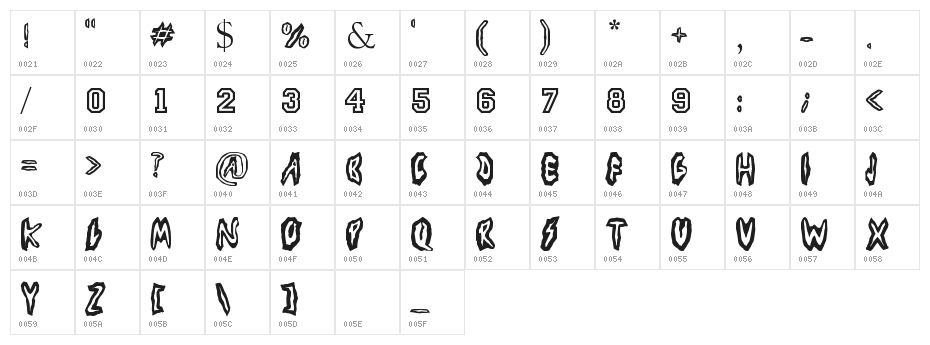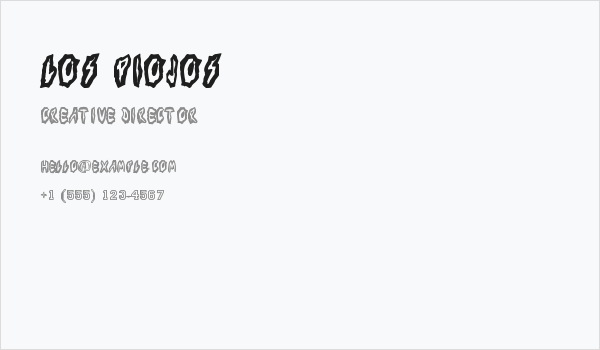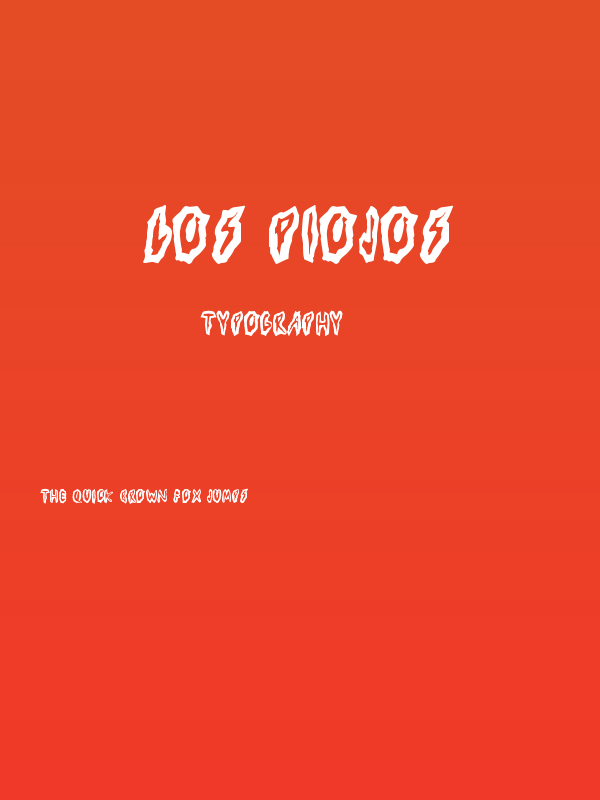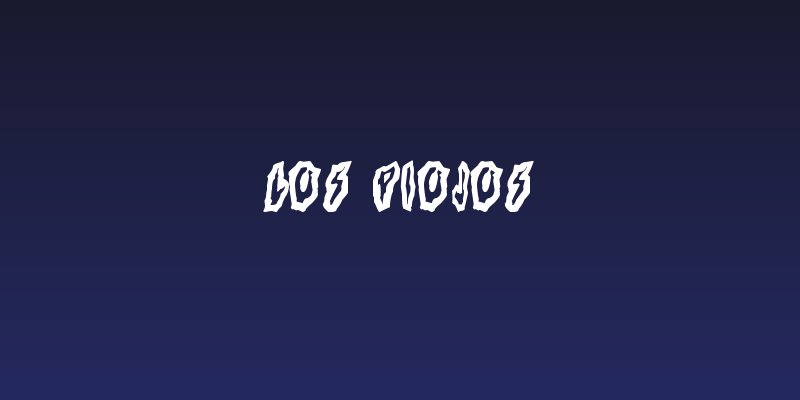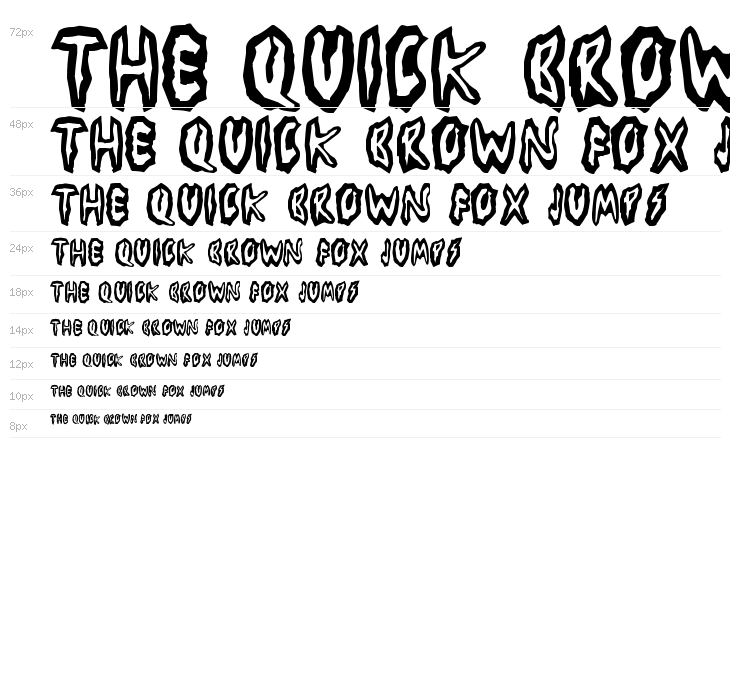
Los Piojos Font
✎ Distorted Eroded
| Kategorien | Distorted Eroded |
| Gesamtstil | Modern, Rebellious |
| Vorgeschlagene Projekte | Ideal for music album covers, posters, streetwear branding, and edgy graphic designs. |